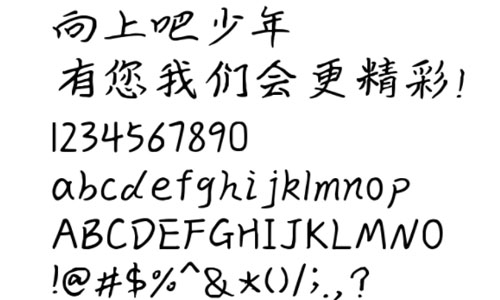
向上吧少年字體是由義啟字庫推出的一款手寫書法字體,字體非常隨性,擁有少年的朝氣,非常向上,能夠應(yīng)用于文本裝潢、信息展示、網(wǎng)頁設(shè)計、篆刻制模、數(shù)據(jù)制作、裝潢設(shè)計、計算藝術(shù)設(shè)計、視覺設(shè)計、字帖等一切合法應(yīng)用場景。歡迎有需要的朋友前來下載使用。